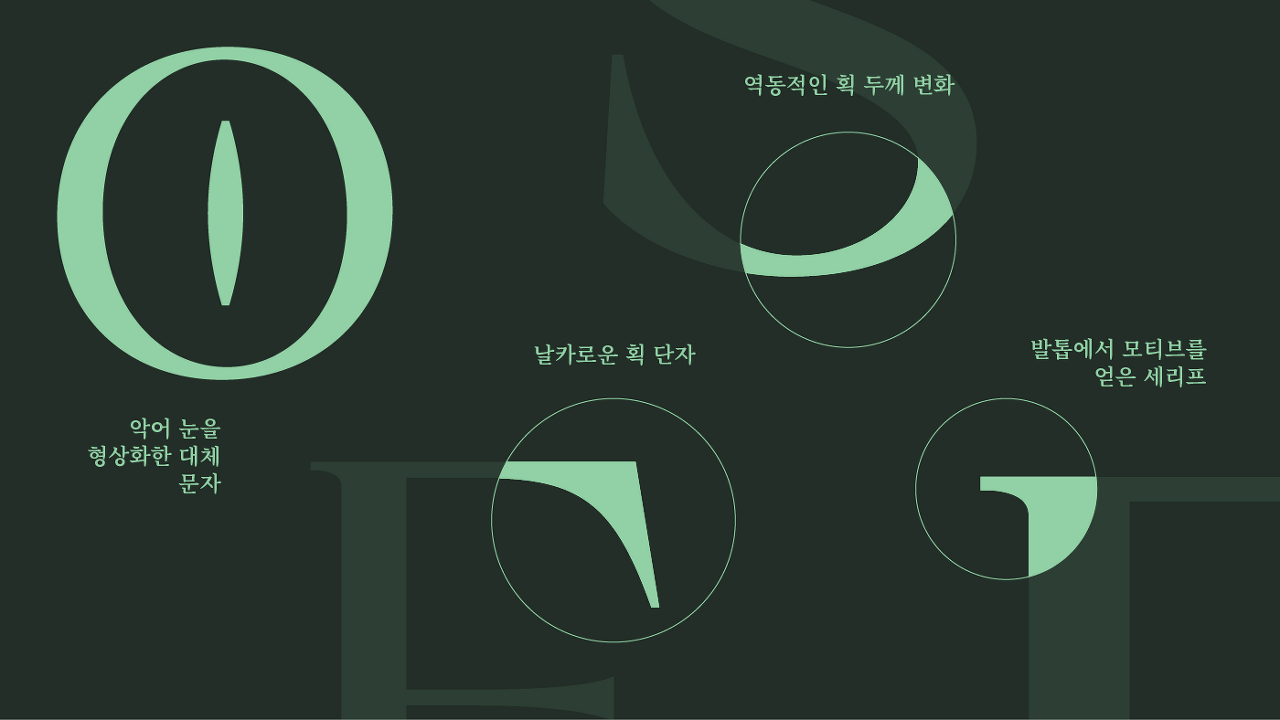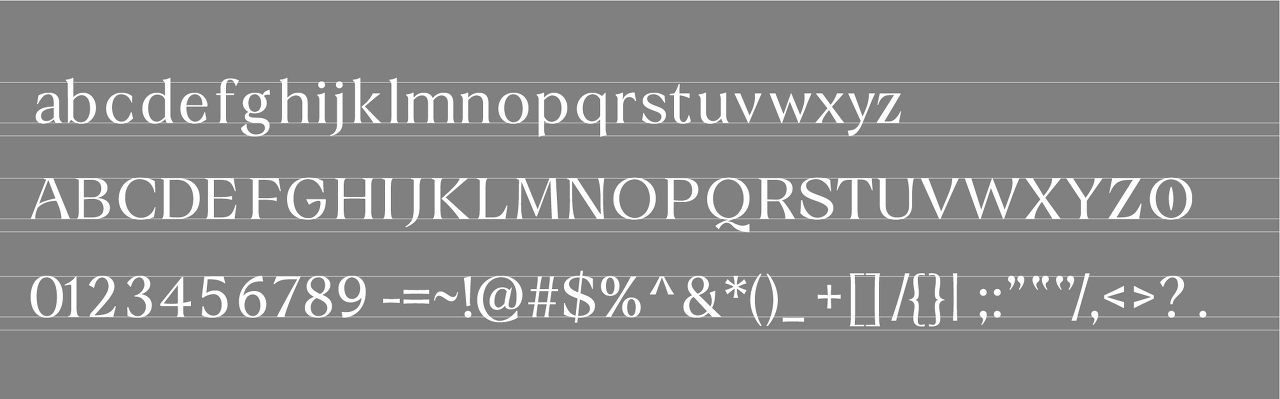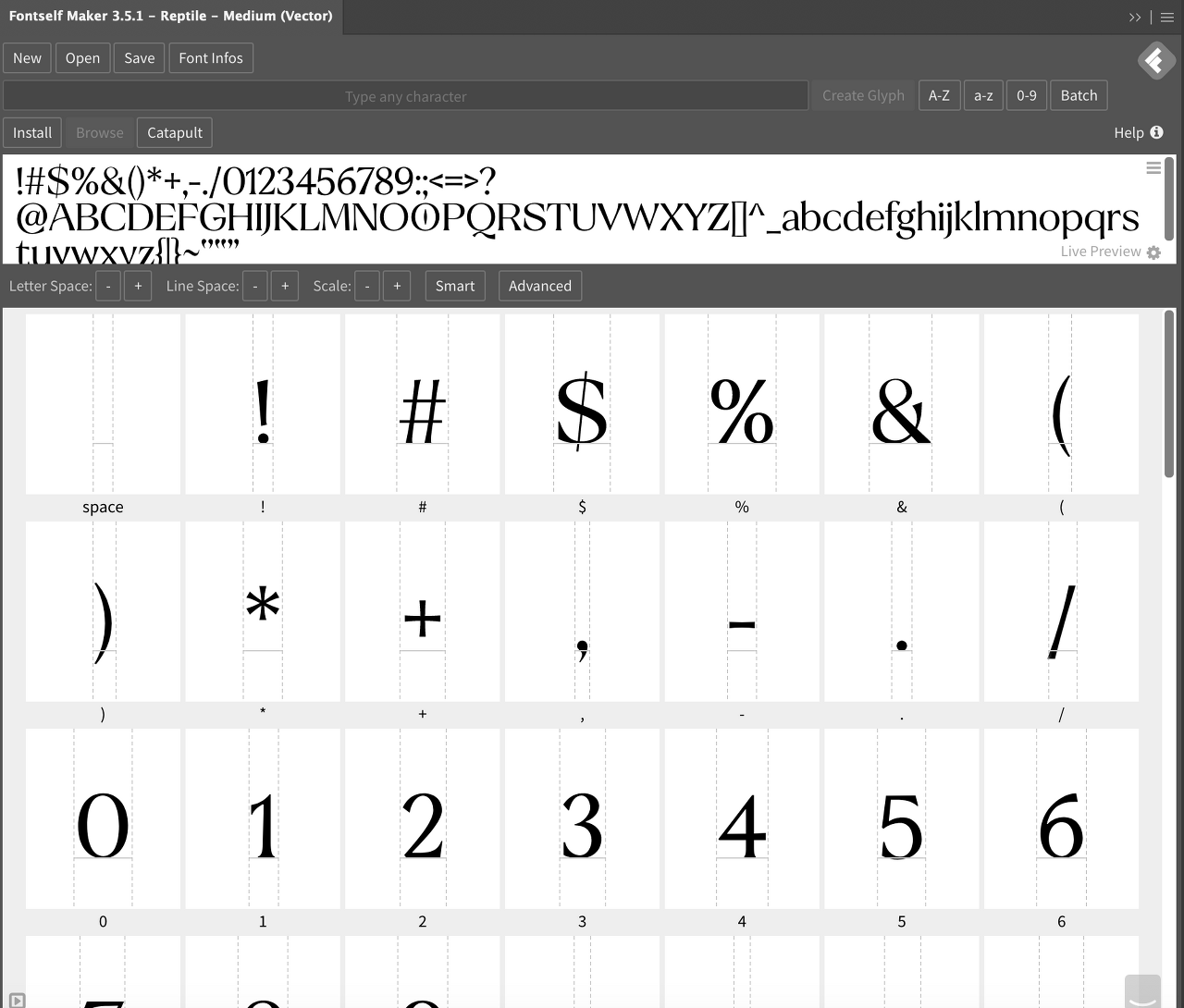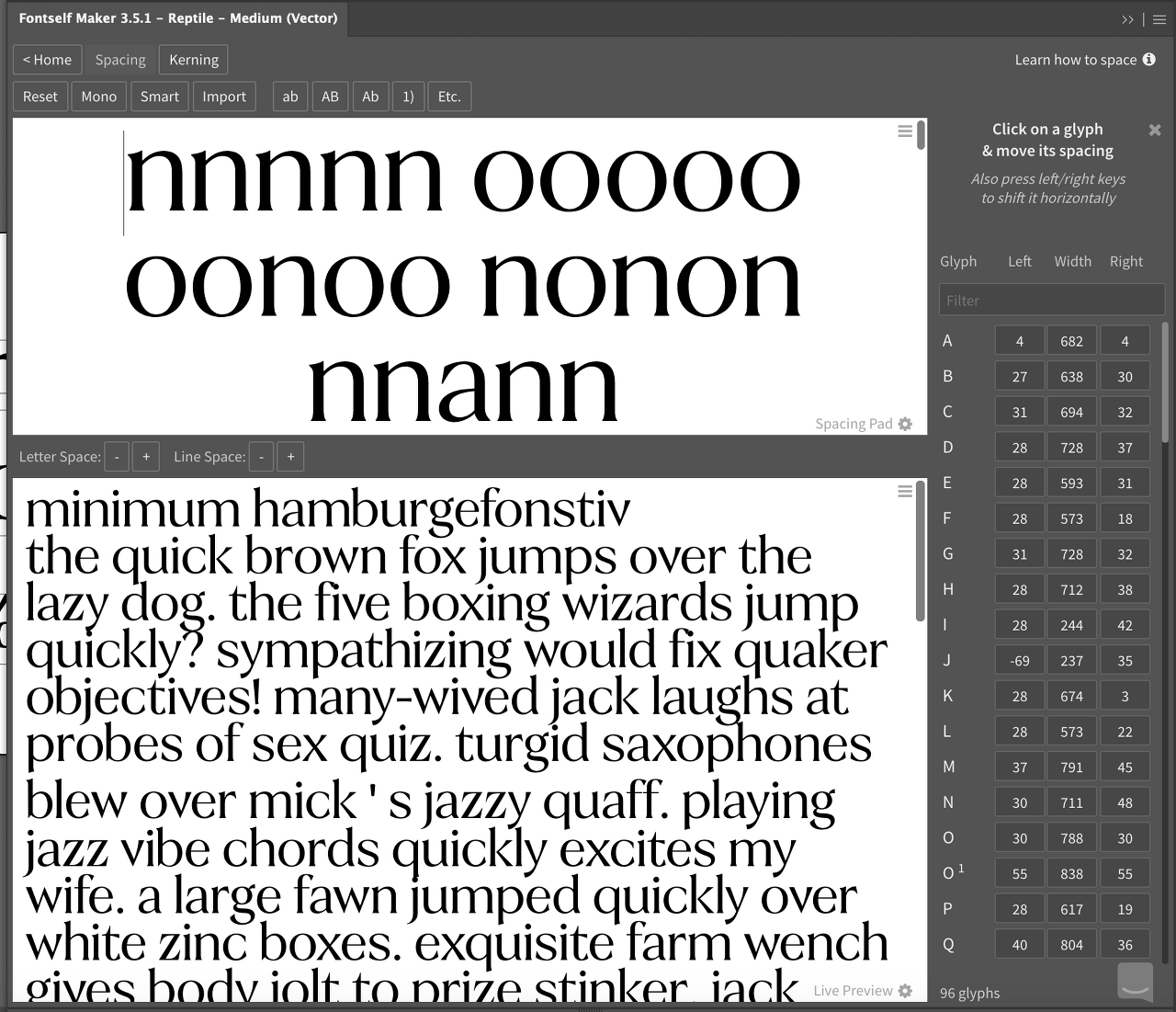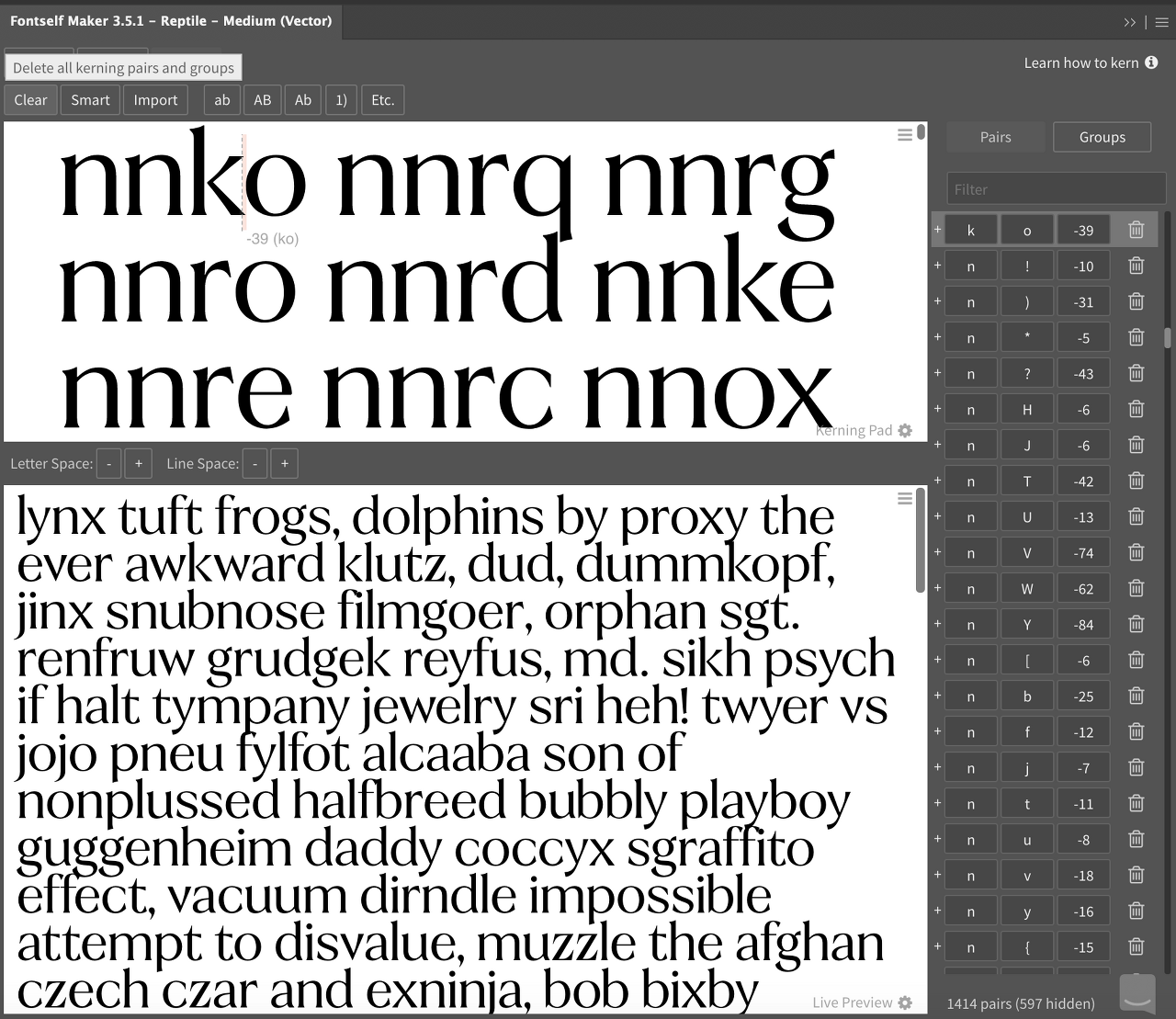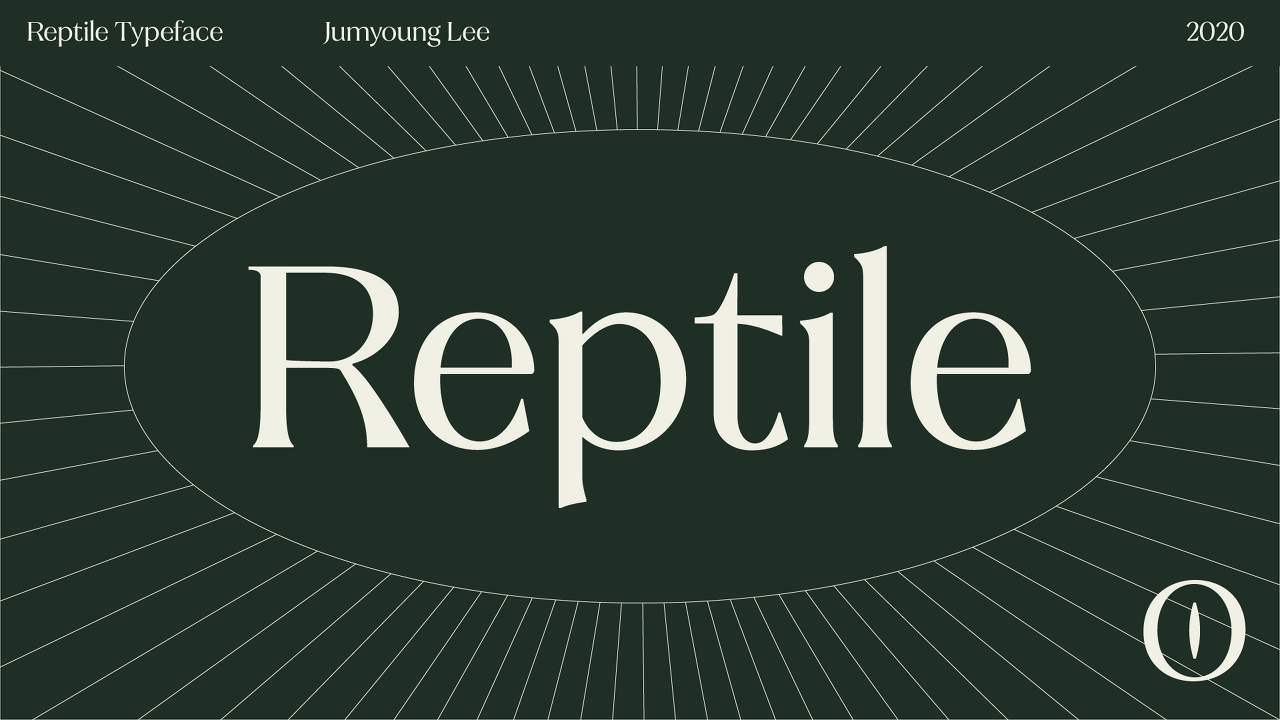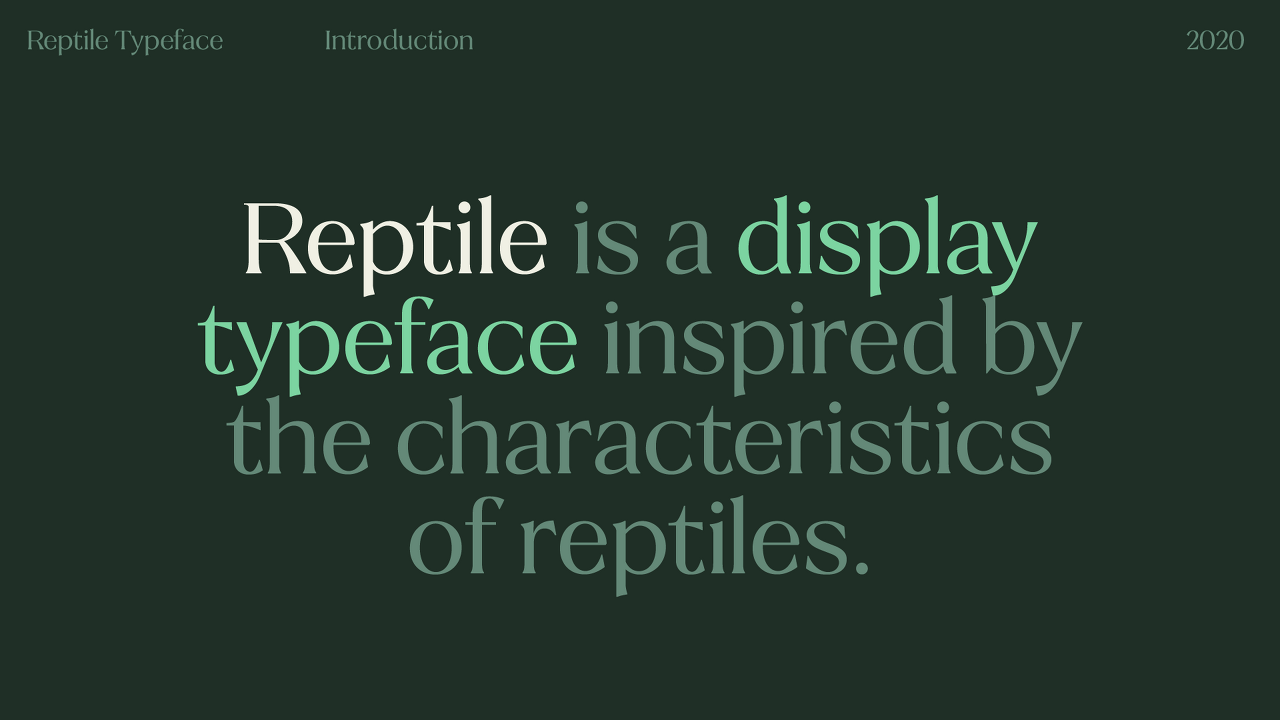
Reptile 폰트 제작기
영문 폰트, 어떻게 만드나요?
개인 프로젝트로 진행했던 Reptile 서체가 Behance 그래픽 디자인 부분에서 Featured 되어 간단한 제작기를 공유해볼까 합니다.
사실 영문이 국문에 비해 자수가 적다고 해도, 아무런 참고 자료 없이 처음부터 글자 디자인을 제작하는 일은 쉽지 않습니다. 모든 글자가 서로 조화를 이루고, 단어, 문장, 문단으로 활용될 때 어색함이 없어야 하기 때문이죠. 따라서 서체 디자이너들은 실제 디자인에 앞서, 아래 두 가지 방식 중에 하나를 택합니다.
유형 1: 기존의 전통 양식을 기반
영문 폰트는 그 역사에 맞게 시대에 따라 비슷한 특징들을 공유하는 스타일들이 있습니다. Transitional Serif 같은 스타일이 그 예죠. 역사적으로 검증되었기 때문에 사람들에게도 친숙하고 상업적으로 활용되기 좋다는 장점이 있습니다.
유형 2: 컨셉을 기반으로 하는 새로운 형태
반대로 기존 전통 양식을 따르지 않고 컨셉을 기반으로 전혀 새로운 형태로 글자를 디자인하는 경우도 있습니다. 보다 실험적이고, 디자이너의 아이디어를 자유롭게 표현할 수 있다는 것이 특징이죠. 이번 글에서 소개드릴 프로젝트는 바로 이 두 번째 유형에 속합니다.
그럼 바로 제작기로 넘어가 볼까요?
1. 컨셉 정하기
이전 글에서도 반복적으로 서체는 디자이너가 표현하고자 하는 뉘앙스를 전달하는 시각적인 언어라고 표현한 적이 있습니다. 하지만 이번 프로젝트는 서체가 디자인의 성격을 표현하기 위한 수단이 아니라, 어떤 것에서 영감을 받고, 그 자체를 표현해보고 싶다는 취지에서 시작했습니다. 그렇게 고르게 된 주제가 파충류였고요! 파충류를 그렇게 좋아하지는 않지만... 다른 동물들보다 재밌는 특징들이 많다고 생각했습니다 :)
우선적으로 단계로 뱀, 도마뱀, 악어와 같은 파충류들의 이미지를 모아 무드 보드를 제작했습니다.
2. 키워드로 도출하기
이전 단계에서 만든 무드 보드에서 파충류의 특징을 아이디어로 구체화하기 위해 키워드로 뽑아봤습니다. 이런 방식은 언제든 다시 아이디어들을 머릿속으로 정리할 수 있고, 초기 콘셉트가 흔들리지 않게 단단히 유지할 수도 있어 추천드리는 방법입니다.
3. 글자로 표현하기
이번에는 이전 과정에서 뽑은 키워드를 바탕으로 글자를 디자인하는 과정입니다. 이 과정에서 저는 한 글자도 여러 스타일로 만들어보고, 하나를 사용하기로 정해도 나머지 글자들을 ‘킵’Keep해두는 편입니다. (나중에 다른 글자들과 대조하며 디테일을 조정할 때 필요하거나, 다른 서체를 디자인할 때도 쓸 수 있기 때문)
4. 다른 글자와 비교하며 통일감 맞추기
글자를 하나하나 다 디자인했다면, 이제를 서로 옆에다 두고 비교할 시간입니다. 글자들이 모여서 하나의 폰트로 사용되기 위해서는 통일감이 그 무엇보다 중요하기 때문이에요. 이 과정에서 글자들의 디테일을 다시 수정해서 서로 조화를 이룰 수 있게 합니다.
5. 폰트 프로그램에 등록하기
글자를 다 완성했다면, 이제 폰트로 활용할 수 있게 폰트 제작 툴에 글자들을 등록하는 과정입니다. 저는 이번 프로젝트에서 일러스트레이터의 플러그인인 Fontself를 사용했습니다. Fontself는 일러스트레이터만 사용하실 줄 안다면 쉽게 폰트 제작을 할 수 있다는 것이 최대 강점이지만, 아직 개발 초기 단계라 여러 기능들이 부족하기 때문에 앞으로 전문적으로 폰트 제작을 하고 싶으신 분들은 Glyphs나 Robofont를 사용하시는 것을 권장합니다.
5-1. Spacing 조정하기
글자를 등록하고 나서의 다음 단계는 글자들의 간격인 Spacing을 조정하는 일입니다. 최근 Fontself에서 Smart Spacing 기능이 추가되어 사용해봤는데 클릭 한 번에 알아서 간격 조정을 해주어 개인적으로 매우 만족했습니다. (인공눈물 넣어가며 글자 하나하나 간격 조정하던 날들이 기억나네요...)
5-2. Kerning 조정하기
spacing 작업이 끝났다면 다음은 Kerning입니다. 이 또한 Smart Kerning 기능을 사용해봤지만 아직은 이 기능은 완벽하지는 않은듯하여 일부 Kerning Pair는 임의로 다시 제가 조정했습니다. 이 과정이 끝났다면 폰트를 완성하셨다고 보아도 무방합니다.
6. 프레젠테이션 하기 - Type Specimen 제작
폰트를 다 완성했다면 이제 남들한테 보여줄 일만 남았겠죠? 폰트의 특징과 활용을 샘플로 보여주는 일종의 쇼케이스를 Type Specimen이라고 합니다. 이번 프로젝트는 단발성이었기 때문에 따로 전문 Type Specimen처럼 책자 형태로 제작하지 않고, 웹 환경을 고려하여 제작했습니다.
활용 예시 - 명함
활용 예시 - 포스터